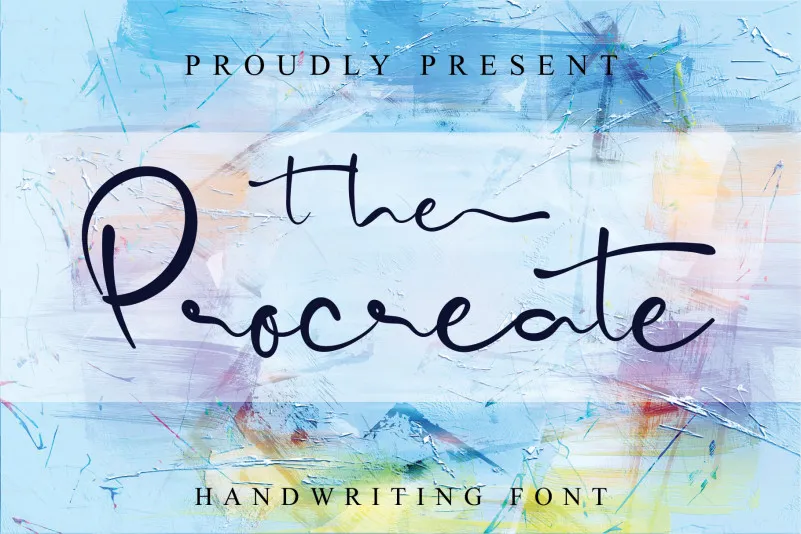
The Procreate Font – Fonte Grátis
The Procreate Font
Esta é uma fonte de escrita filigranada com um tom delicado e elegante. Ela se destaca por seu estilo refinado que transmite sofisticação, perfeitamente adequada para qualquer projeto gráfico. As alternativas estilizadas e ligaturas que ela oferece garantem que seja uma escolha perfeita para aqueles projetos exigentes em requinte. A fonte “The Procreate Font” é perfeita tanto para criações digitais como para obras impressas, dando um toque único e refinado ao seu design. Descubra por si mesmo a sutileza e elegância desta fonte de escrita filigranada com estilo.